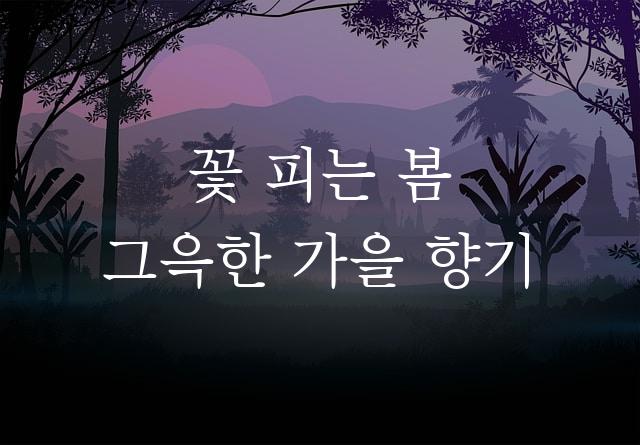
바른돋움체는 대한인쇄문화협회에서 제작한 기본 고딕 폰트로, 세련되면서도 깔끔한 느낌을 제공합니다. 이 폰트는 독서나 문서 작업에 적합하며 어느 상황에서든 잘 어울립니다.
바른돋움체은(는)
기본 고딕, 감성적인, 부드러움 계열의 생김새를 가지고 있으며
웹/앱 디자인, 프레젠테이션, 보고서/문서 등에서 자주 활용되며, 효과적인 메시지 전달에 적합합니다.
이 폰트는 교육, 공공/정부, 금융/비즈니스 분야에 잘 어울리며,
신뢰감, 명확한, 전문적인 느낌을 담고 있는 것이 특징입니다.
이 폰트와 유사한 폰트로는 나눔고딕, 맑은고딕, 서울남산체 등이 있어요. 함께 비교해 보시면 좋습니다!